Balassi Intézet pályázata
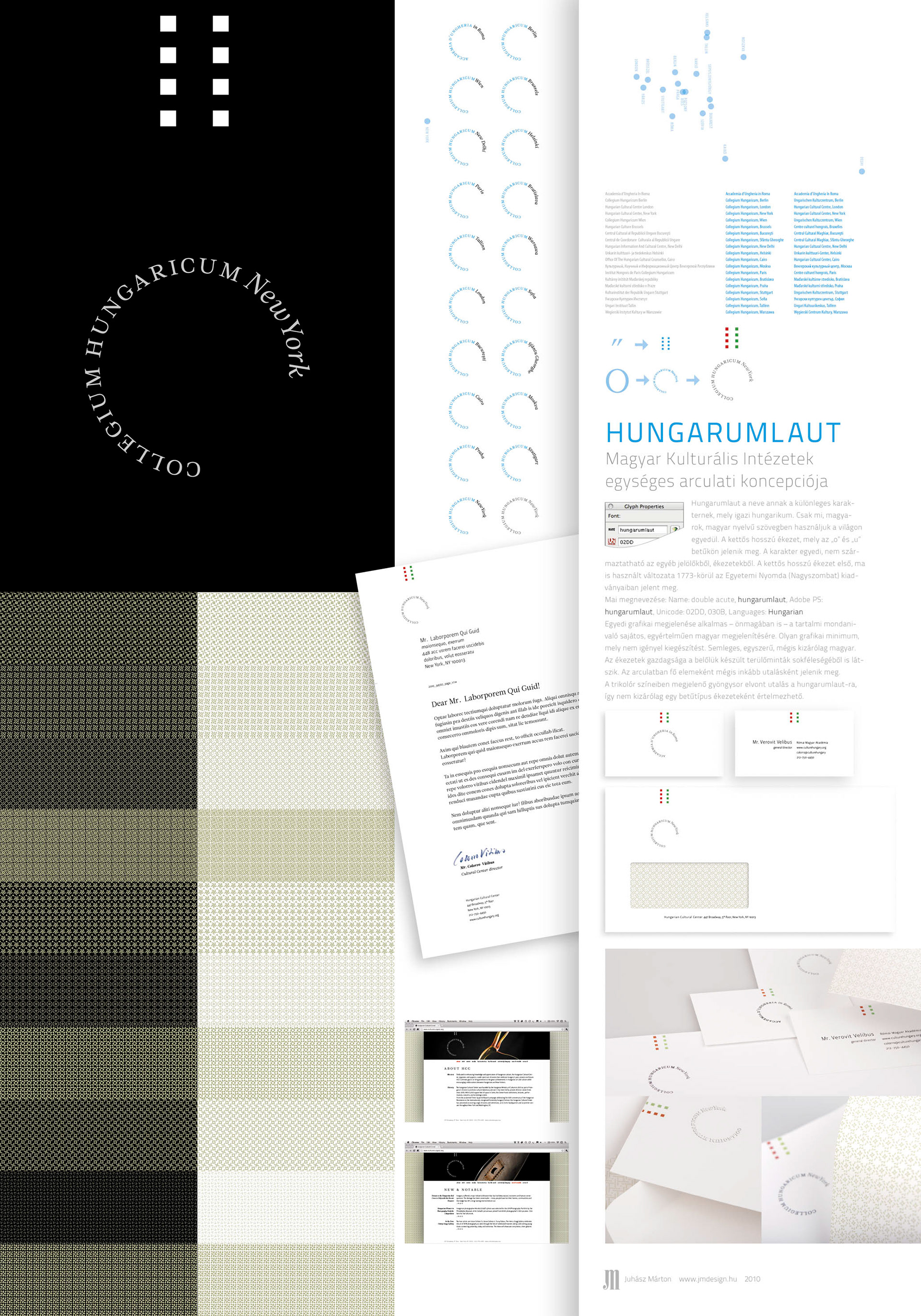
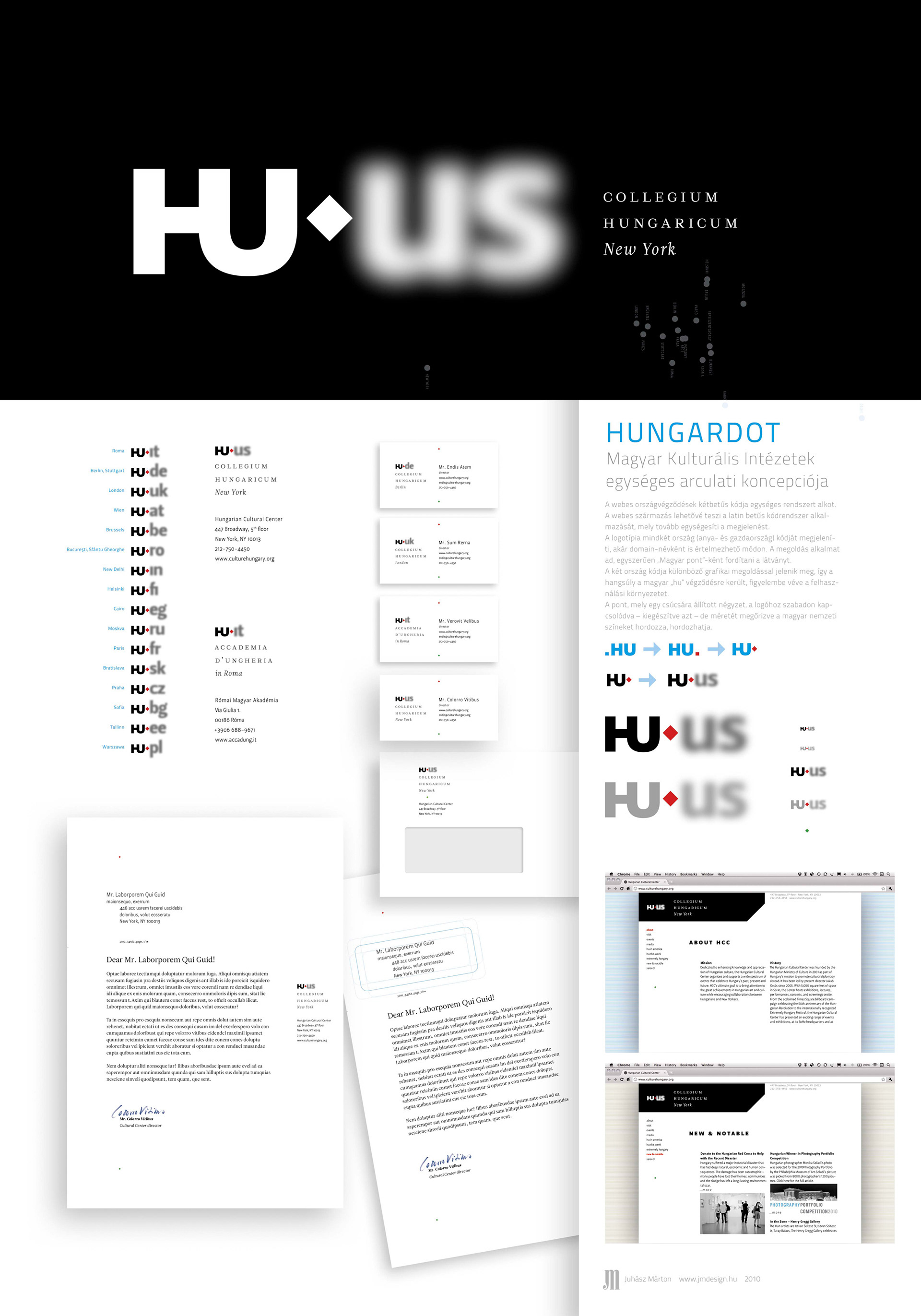
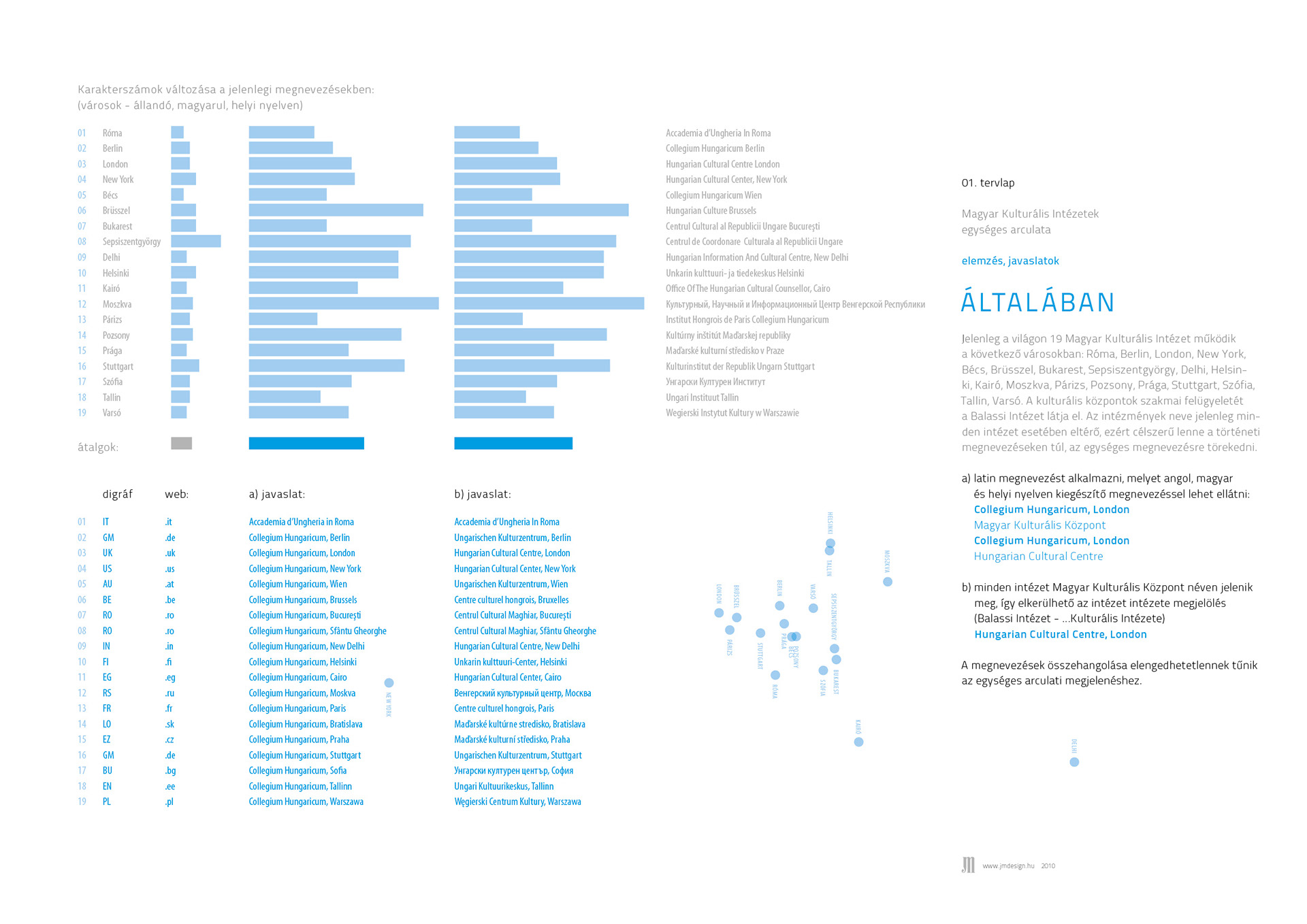
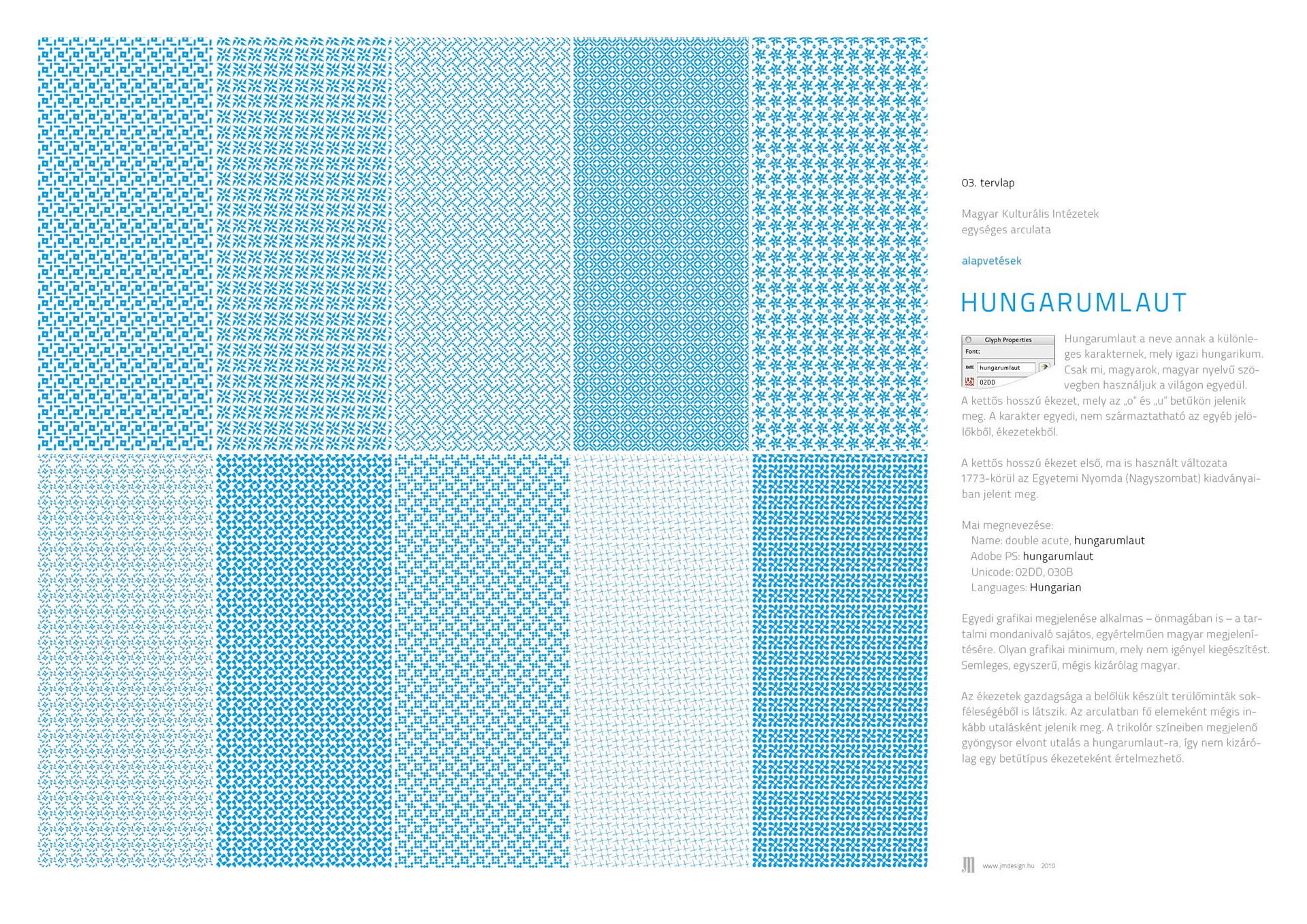
Hungarumlaut a neve annak a különleges karakternek, mely igazi hungarikum. Csak mi, magyarok, magyar nyelvű szövegben használjuk a világon egyedül. A kettős hosszú ékezet, mely az „o” és „u” betűkön jelenik meg. A karakter egyedi, nem származtatható az egyéb jelölőkből, ékezetekből.
A kettős hosszú ékezet első, ma is használt változata 1773-körül az Egyetemi Nyomda (Nagyszombat) kiadványaiban jelent meg.
Mai megnevezése:
Name: double acute, hungarumlaut
Adobe PS: hungarumlaut
Unicode: 02DD, 030B
Languages: Hungarian
Egyedi grafikai megjelenése alkalmas – önmagában is – a tartalmi mondanivaló sajátos, egyértelműen magyar megjelenítésére. Olyan grafikai minimum, mely nem igényel kiegészítést. Semleges, egyszerű, mégis kizárólag magyar.
Az ékezetek gazdagsága a belőlük készült terülőminták sokféleségéből is látszik. Az arculatban fő elemeként mégis inkább utalásként jelenik meg. A trikolór színeiben megjelenő gyöngysor elvont utalás a hungarumlaut-ra, így nem kizárólag egy betűtípus ékezeteként értelmezhető.
A kettős hosszú ékezet első, ma is használt változata 1773-körül az Egyetemi Nyomda (Nagyszombat) kiadványaiban jelent meg.
Mai megnevezése:
Name: double acute, hungarumlaut
Adobe PS: hungarumlaut
Unicode: 02DD, 030B
Languages: Hungarian
Egyedi grafikai megjelenése alkalmas – önmagában is – a tartalmi mondanivaló sajátos, egyértelműen magyar megjelenítésére. Olyan grafikai minimum, mely nem igényel kiegészítést. Semleges, egyszerű, mégis kizárólag magyar.
Az ékezetek gazdagsága a belőlük készült terülőminták sokféleségéből is látszik. Az arculatban fő elemeként mégis inkább utalásként jelenik meg. A trikolór színeiben megjelenő gyöngysor elvont utalás a hungarumlaut-ra, így nem kizárólag egy betűtípus ékezeteként értelmezhető.
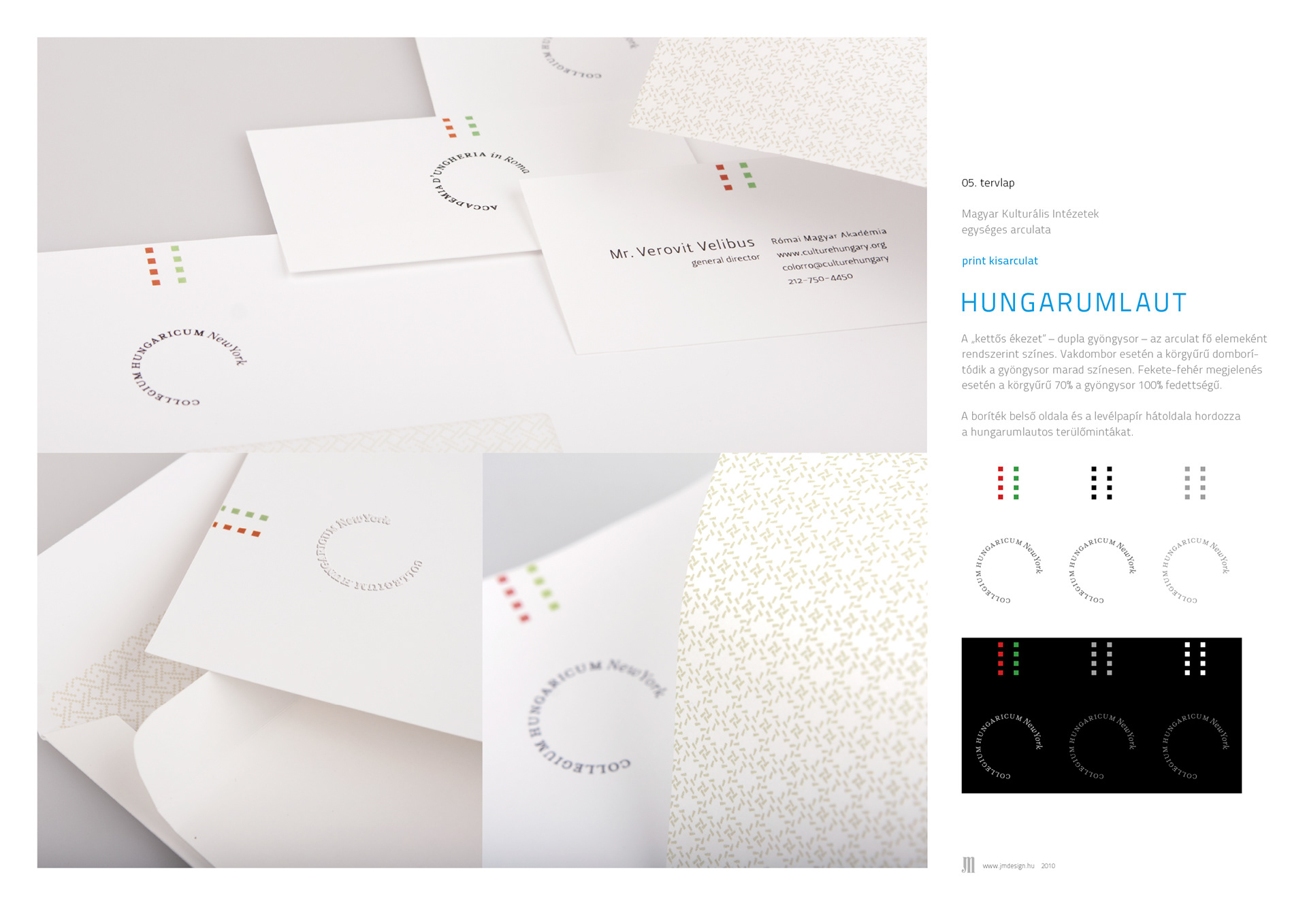
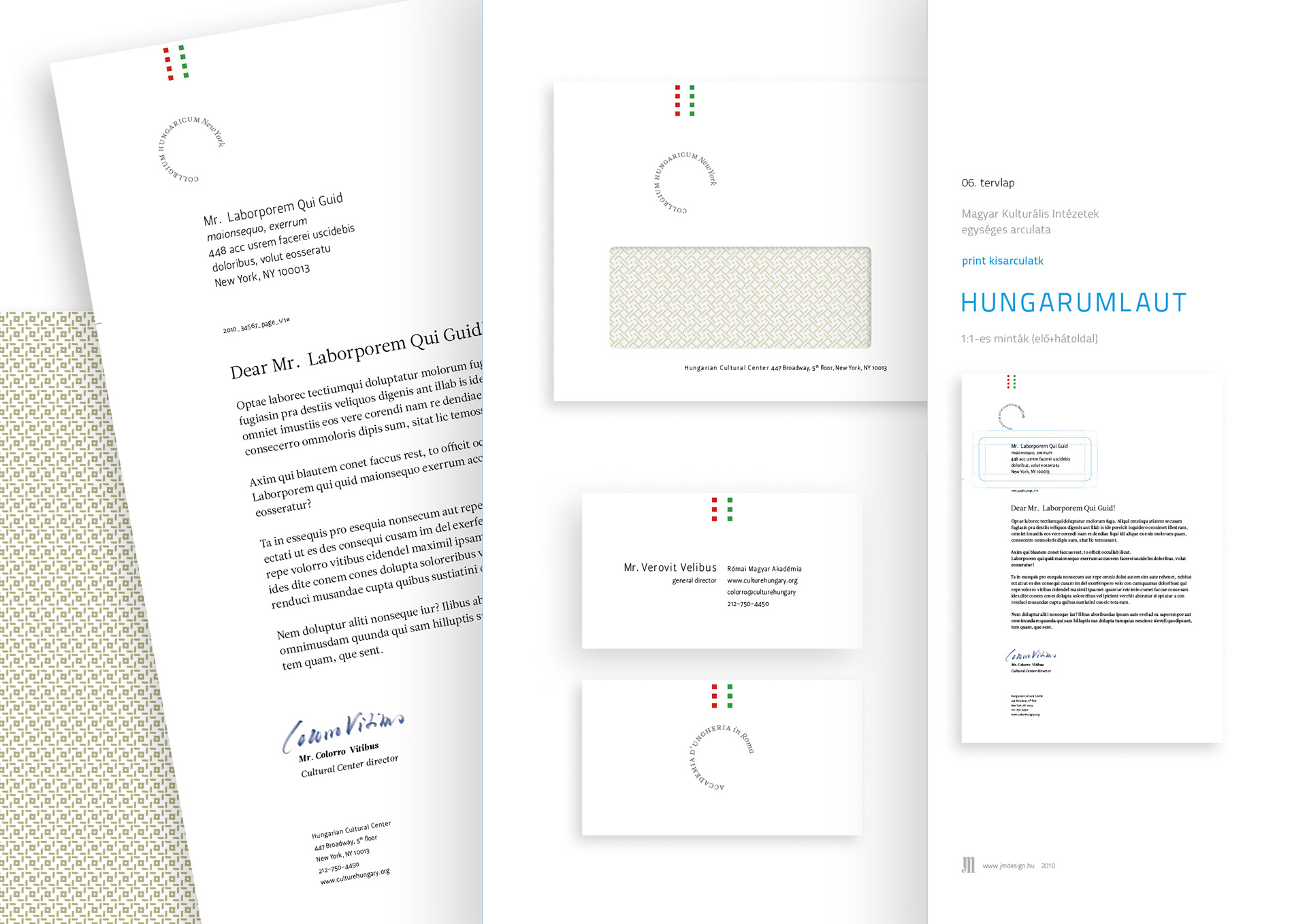
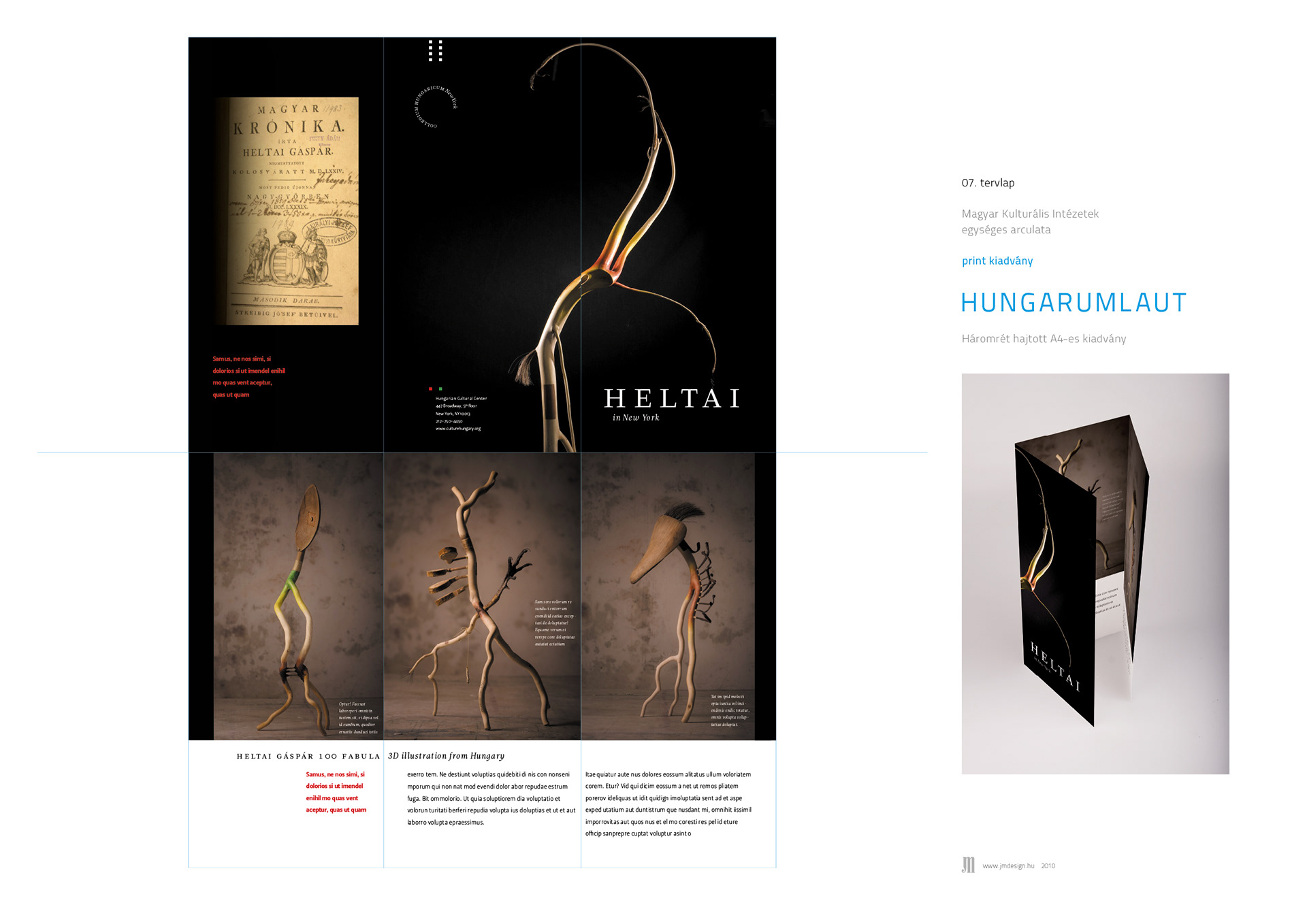
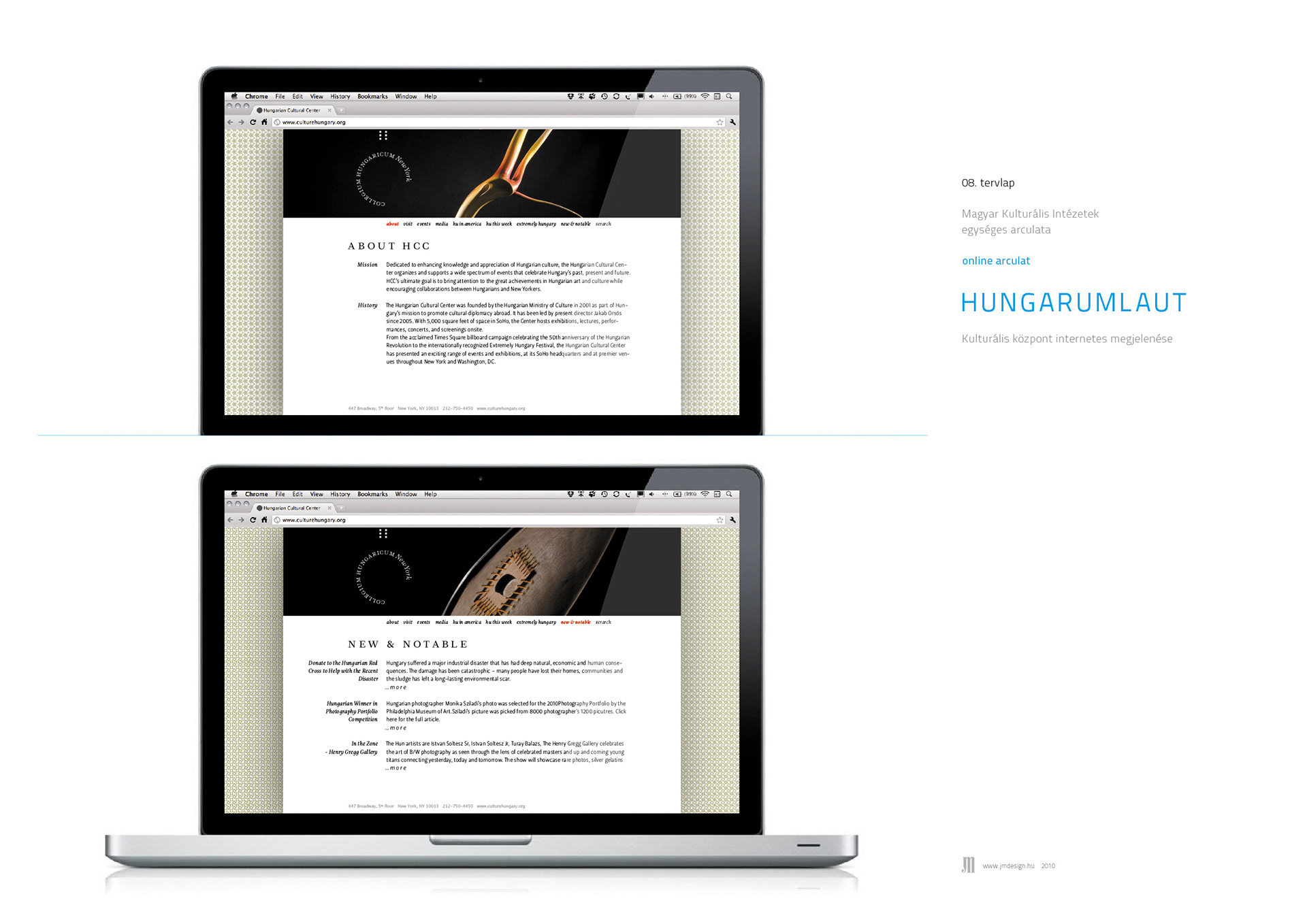
A webes országvégződések kétbetűs kódja egységes rendszert alkot. A webes származás lehetővé teszi a latin betűs kódrendszer alkalmazását, mely tovább egységesíti a megjelenést.
A logotípia mindkét ország (anya- és gazdaország) kódját megjeleníti, akár domain-névként is értelmezhető módon. A megoldás alkalmat ad, egyszerűen „Magyar pont”-ként fordítani a látványt.
A két ország kódja különböző grafikai megoldással jelenik meg, így a hangsúly a magyar „hu” végződésre került, figyelembe véve a felhasználási környezetet.
A pont, mely egy csúcsára állított négyzet, a logóhoz szabadon kapcsolódva – kiegészítve azt – de méretét megőrizve a magyar nemzeti színeket hordozza.
A logotípia mindkét ország (anya- és gazdaország) kódját megjeleníti, akár domain-névként is értelmezhető módon. A megoldás alkalmat ad, egyszerűen „Magyar pont”-ként fordítani a látványt.
A két ország kódja különböző grafikai megoldással jelenik meg, így a hangsúly a magyar „hu” végződésre került, figyelembe véve a felhasználási környezetet.
A pont, mely egy csúcsára állított négyzet, a logóhoz szabadon kapcsolódva – kiegészítve azt – de méretét megőrizve a magyar nemzeti színeket hordozza.